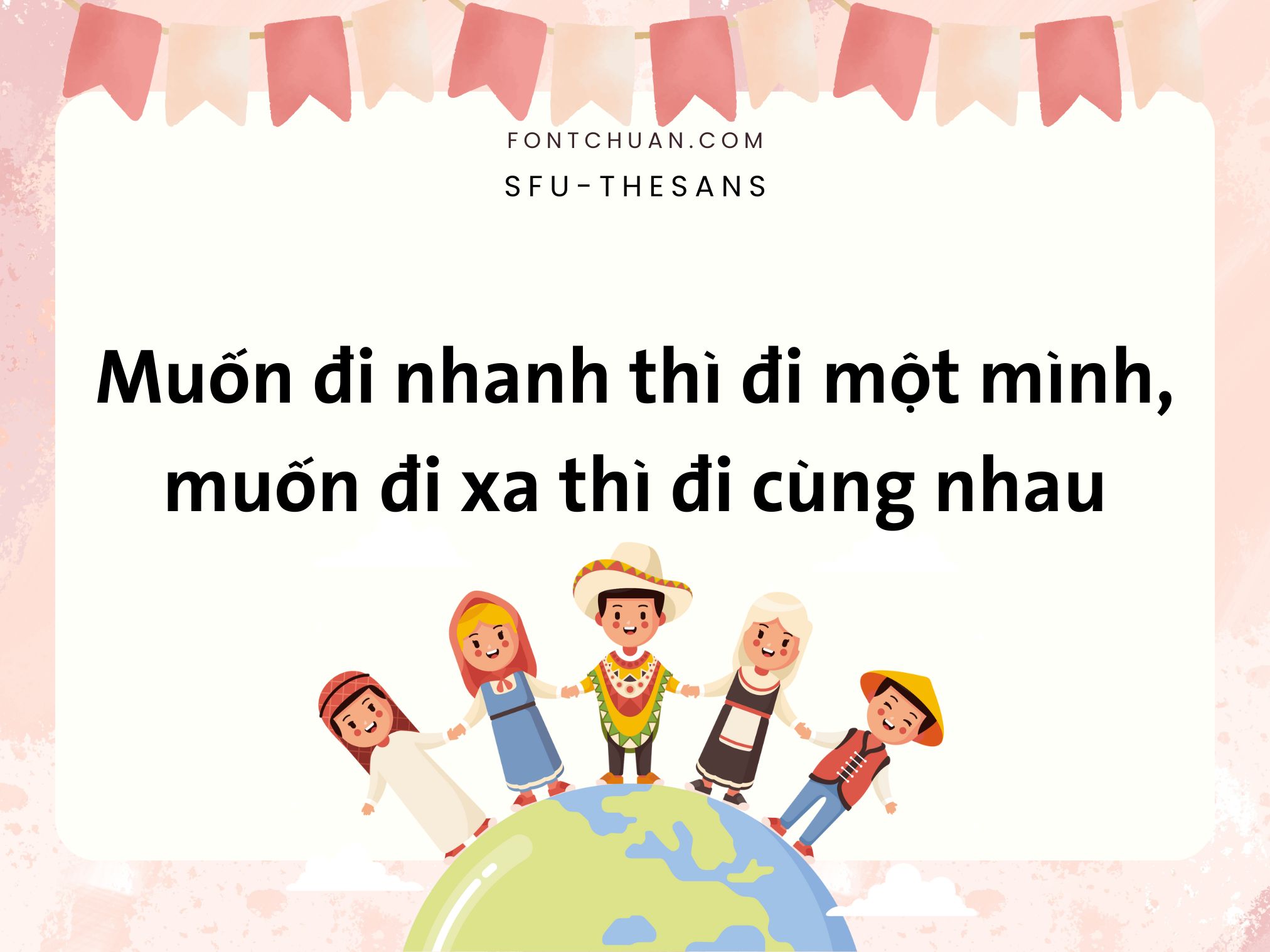
Font SFU Thesans Việt Hóa
Font SFU TheSans là một kiểu chữ sans-serif hiện đại, được thiết kế với các đường nét rõ ràng và cân đối, tạo cảm giác chuyên nghiệp và dễ đọc. Font này hỗ trợ tiếng Việt và phù hợp cho nhiều mục đích sử dụng khác nhau, từ văn bản nội dung đến tiêu đề và thiết kế đồ họa.
SFU TheSans lý tưởng cho các dự án thiết kế logo, tiêu đề, bao bì sản phẩm và các ấn phẩm quảng cáo. Các ngành nghề như quảng cáo, giáo dục và công nghệ có thể tận dụng font này để tạo điểm nhấn trong thiết kế. Ngoài ra, font cũng thích hợp cho các sự kiện như Tết, Giáng sinh, Valentine và các lễ hội khác.